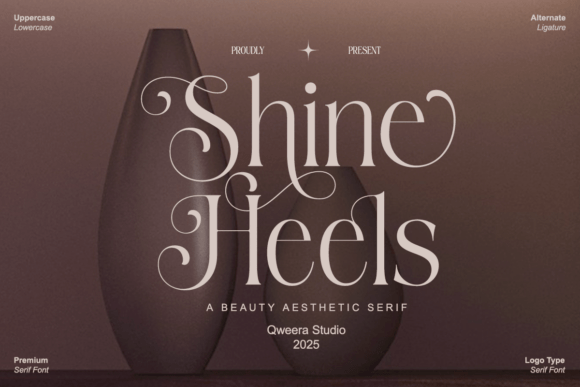
Shine Heels
適切なデザイン要素を見つけるのは難しい場合がありますが、Shine Heelsは作品を即座に引き立てる優れたコレクションを提供します。
精密に作られたShine Heelsは、クリーンなベクター、滑らかなタイポグラフィ、そして安心のための商用ライセンスを提供します。
POD(オンデマンド印刷)製品、結婚式の招待状、またはソーシャルメディアのグラフィックを作成している場合でも、Shine Heelsは理想的です。